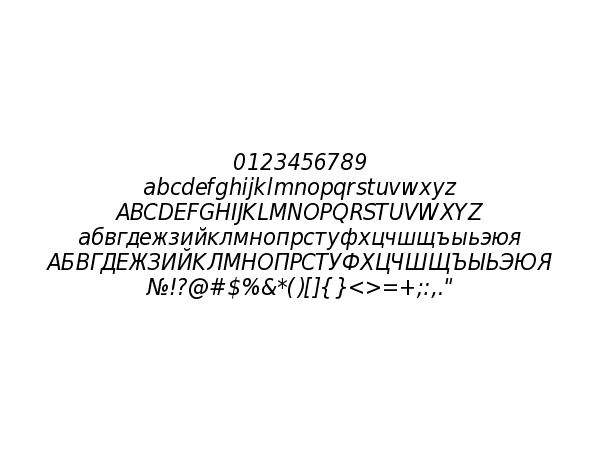
DejaVu Sans Condensed Oblique CP1251 и
DejaVu Serif Condensed Oblique CP1251
DejaVu Sans Condensed Oblique CP1251 and
DejaVu Serif Condensed Oblique CP1251
ОПИСАНИЕ
Шрифтовете DejaVu Sans Condensed Oblique CP1251 и DejaVu Serif Condensed Oblique CP1251 са кирилски шрифтове в кодировка Windows-1251 и произхождат от свободните шрифтове DejaVu Sans Condensed Oblique и DejaVu Serif Condensed Oblique. Направих ги за създаване на векторни графики с кирилица във SWF (флаш) формат чрез програмата ploticus. Флаш версията на шрифтовете (FDB файлове) също е включена в архивите, както и изходния код. На настоящия етап шрифтовете не са подходящи за използване в текстообработващи програми.
DejaVu Sans Condensed Oblique CP1251
DejaVu Serif Condensed Oblique CP1251
DejaVu Sans Condensed Oblique CP1251 and
DejaVu Serif Condensed Oblique CP1251
DESCRIPTION
DejaVu Sans Condensed Oblique CP1251 and DejaVu Serif Condensed Oblique CP1251 are Windows-1251 encoded cyrillic fonts derived from the free fonts DejaVu Sans Condensed Oblique and DejaVu Serif Condensed Oblique. I made them for producing Cyrillic SWF (Flash) graphics using ploticus ploting and charting program. Flash fonts (FDB files) are also included, as well as the source code. The supplied fonts are currently not suitable for use in wordprocessing software.
DejaVu Sans Condensed Oblique CP1251
DejaVu Serif Condensed Oblique CP1251